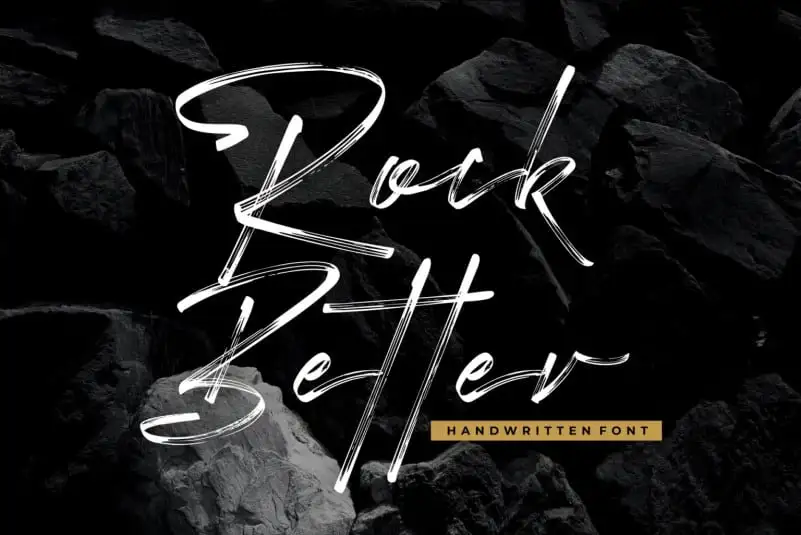
Rock Better Brush Font
A Rock Better Brush Font é uma opção perfeita para quem busca um estilo elegante e chamativo. Com a textura desajeitada do seu design, esse script brush ganha uma dose extra de glamour adequado tanto para headlines quanto para logotipos e assinaturas. Seja você criando cartazes de marketing, desenvolvendo um site ou mesmo produzindo conteúdo online, esta fonte oferece a oportunidade de destacar sua marca com um toque único e imponente. Conforme mencionado na descrição original em inglês, essa fonte traz todo o brilho necessário para complementar qualquer projeto que exija uma atitude diferenciada. Seja você designer gráfico ou criador de conteúdo digital, a Rock Better Brush Font é uma escolha inteligente para capturar a atenção da sua audiência.